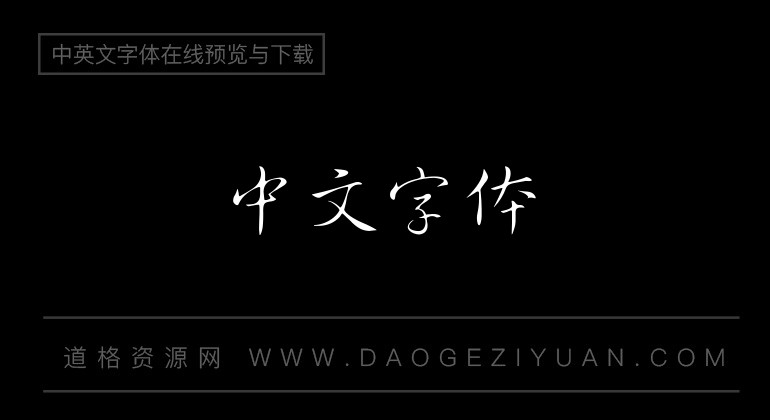
銳字工房雲字庫行草字體是一款簡潔的行草字體,它結合了行草字體的傳統風格和現代感,以及精細的細節,為您的文字帶來更多的靈動性和活力。它為您提供了豐富的字形細節,以及完整的漢字支持,使您的文字更具視覺衝擊力。此外,它還支持多種字體格式,可以讓您在任何設備上使用,從而讓您的文字更加美觀大方。
是一款非常不錯的手寫藝術字體,具有很好的視覺感,適合於文化類的宣傳設計、商業類品牌的廣告和產品包裝設計以及個性化文字排版等較多場景。